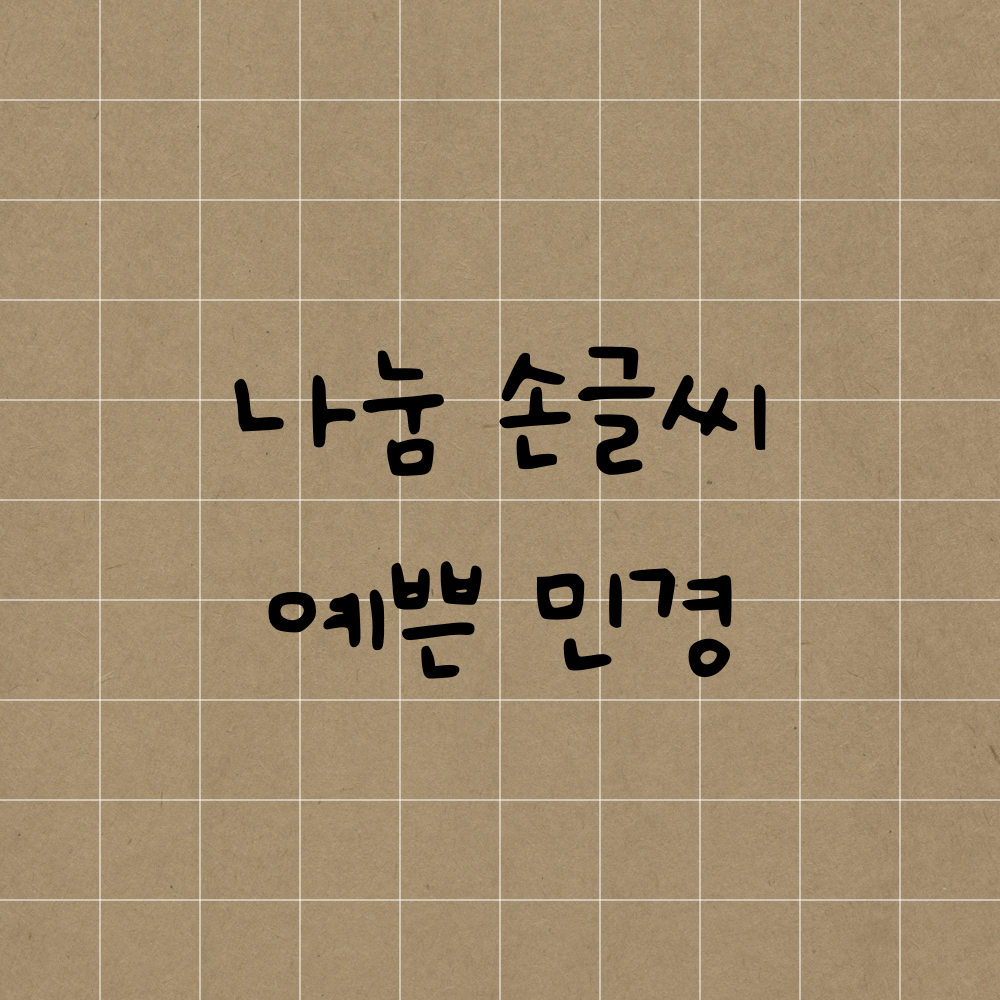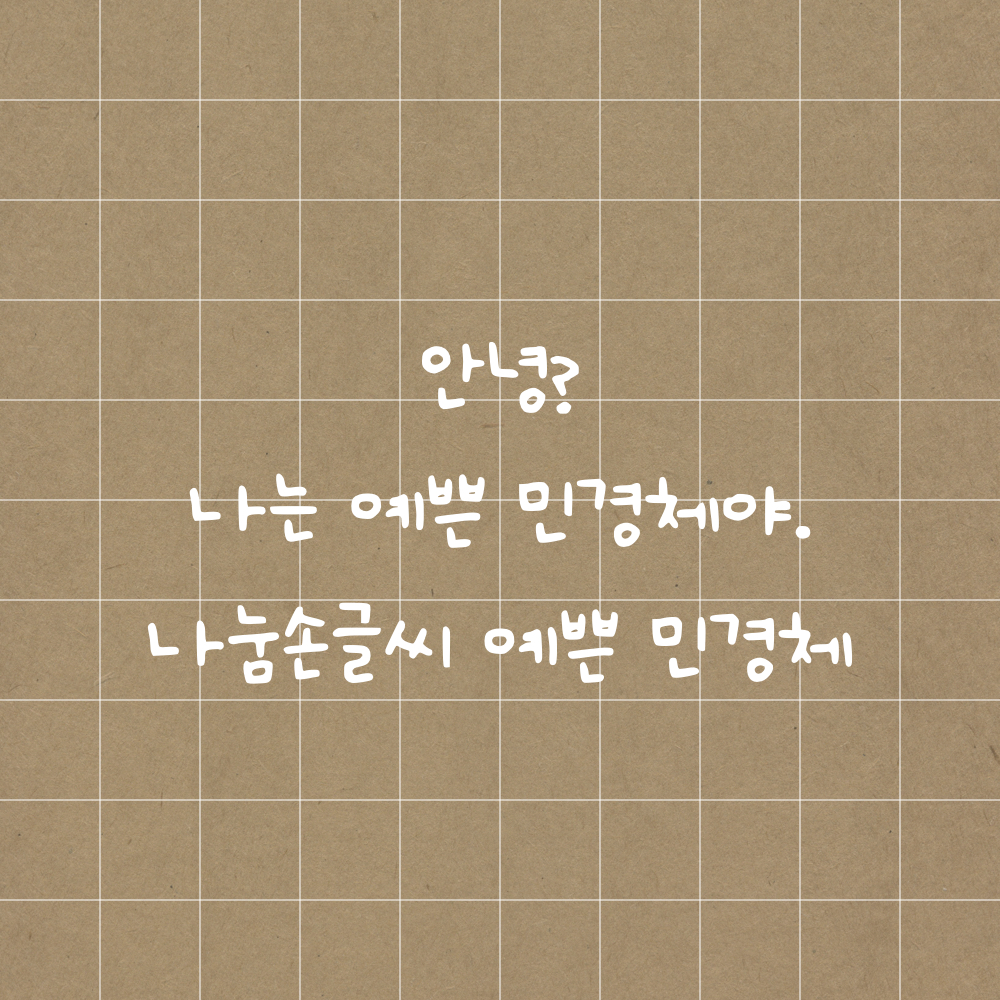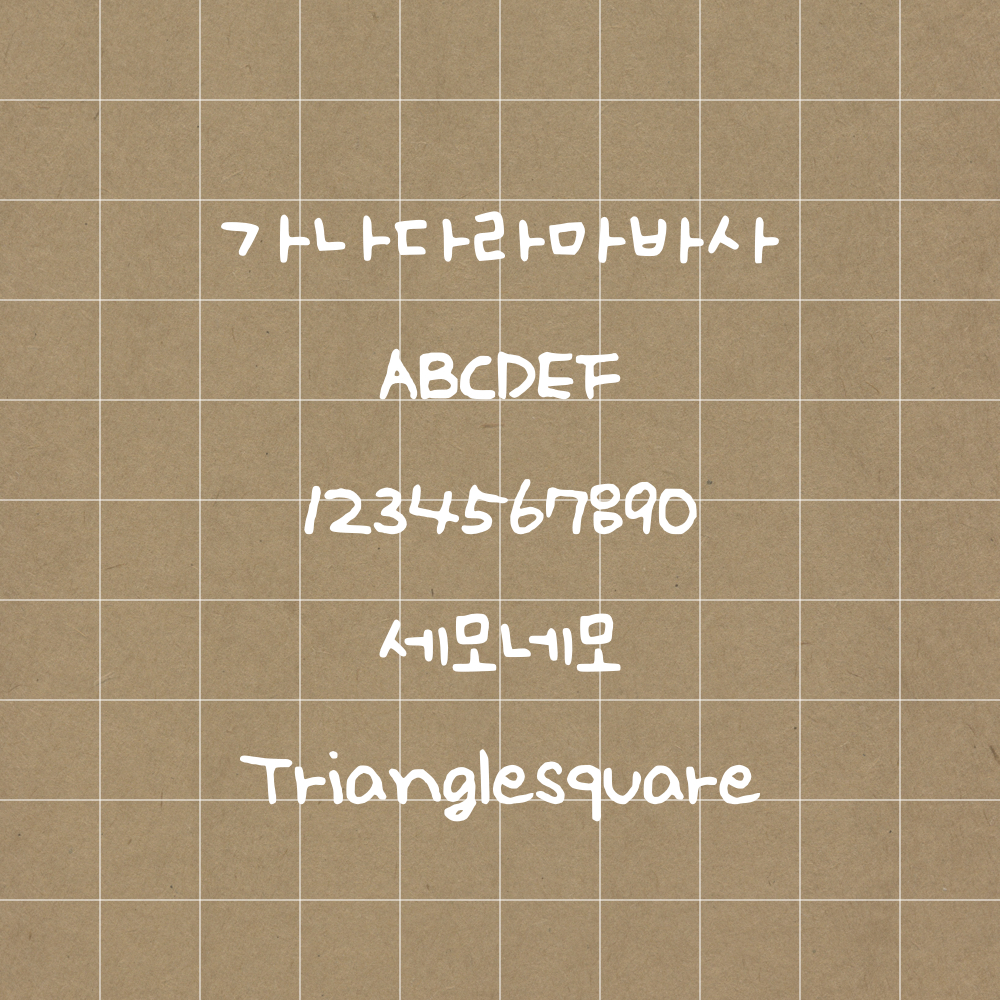
오늘의 폰트는 예쁜 민경체입니다❤️
아기자기한 다꾸를 즐기는 분들께 무한 사랑을 받는 폰트입니다😘
한국어와 영어를 모두 지원합니다. 그럼 예시를 한 번 살펴볼까요?
프로 다꾸러일 때 저의 글씨체와 분위기가 다른 폰트라서 자주 사용한 기억이 나네요.곰돌이, 꽃, 새싹이랑 참 잘어울리는 폰트로 스티커북에 아기자기한 스티커가 많다면예쁜 민경체로 다꾸를 해보는건 어떤가요~?💕